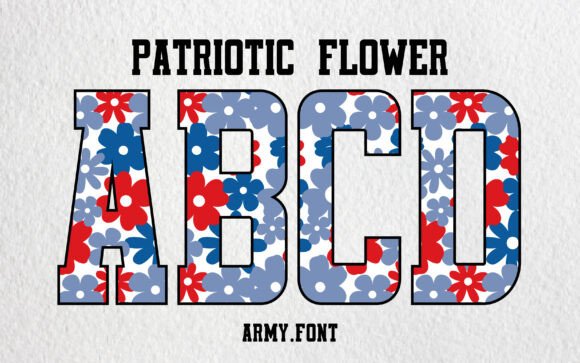
Patriotic Flower
Att hitta rätt designelement kan vara utmanande, men Patriotic Flower erbjuder en exceptionell samling som omedelbart lyfter ditt arbete.
Oavsett om du skapar POD-produkter (Print on Demand), bröllopsinbjudningar eller grafik för sociala medier, är Patriotic Flower ett perfekt val.